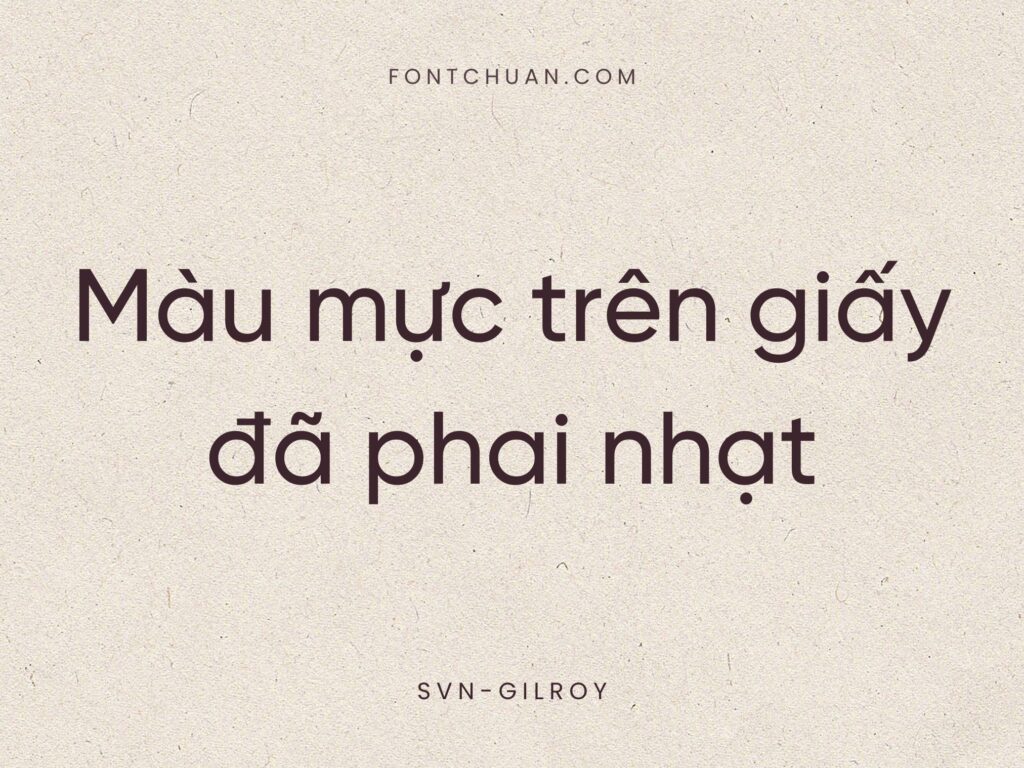
Font SVN Gilroy là phiên bản Việt hóa của kiểu chữ Gilroy, được thực hiện bởi Styleno.1 Fonts. Gilroy là một kiểu chữ sans-serif hiện đại với cấu trúc hình học rõ ràng, được thiết kế bởi Radomir Tinkov. Với đường nét cân đối, độ dày đa dạng và độ tương phản thấp, font này mang đến sự linh hoạt cao trong thiết kế, từ nội dung văn bản đến tiêu đề thương hiệu. Gilroy đã được sử dụng trong nhiều dự án thương hiệu và truyền thông trên toàn thế giới nhờ khả năng thích ứng tốt với các nền tảng thiết kế số và in ấn.
SVN Gilroy phù hợp cho các dự án thiết kế chuyên nghiệp như logo, tiêu đề, tài liệu thương hiệu và các ấn phẩm marketing. Font đặc biệt hiệu quả trong lĩnh vực quảng cáo, công nghệ và giáo dục, giúp truyền tải thông điệp một cách rõ ràng và hiện đại. Ngoài ra, kiểu chữ này cũng phù hợp với các sự kiện như Tết, Giáng sinh, Valentine và các dịp lễ hội cần một phong cách hiện đại, trẻ trung và trực quan.